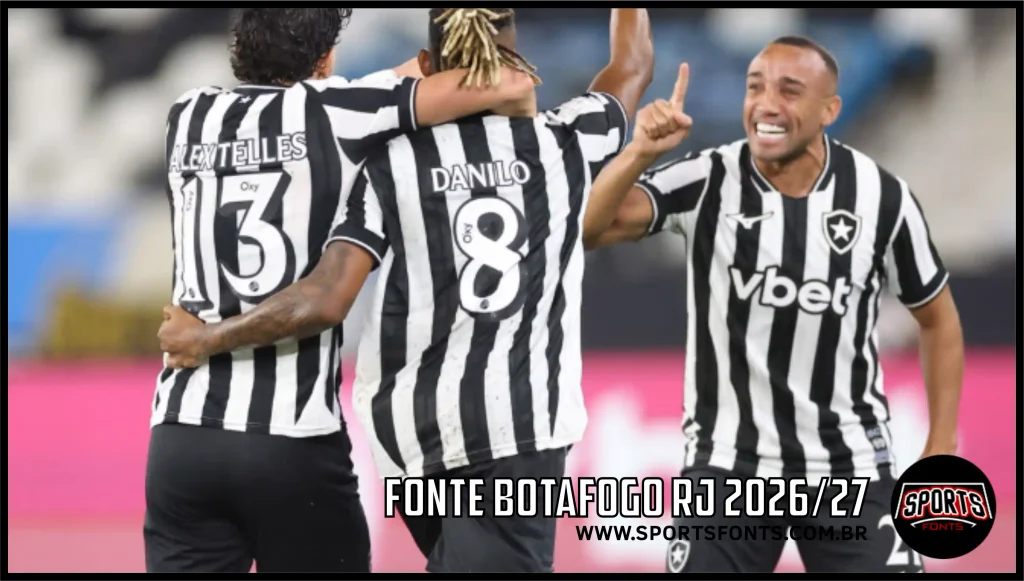
O Botafogo 2026/27 ganhou uma nova versão de sua tipografia esportiva no SportsFonts. Confira os números e letras vetorizados e faça o download gratuito para seus projetos.
Fonte Botafogo RJ 2026/27: versão vetorizada para download
Os torcedores do Botafogo de Futebol e Regatas que gostam de personalizar camisas e criar artes esportivas já podem conferir uma nova opção no SportsFonts: uma versão vetorizada da tipografia de nomes e números associada ao uniforme do clube na temporada 2026/27.
O material foi desenvolvido a partir da análise visual da numeração e das letras presentes na camisa, com o objetivo de reproduzir suas principais características gráficas e facilitar a utilização em projetos de design esportivo.
Características da tipografia Botafogo 2026/27
A numeração analisada apresenta um estilo esportivo marcante, com elementos que ajudam a destacar os algarismos nas costas da camisa.
Entre as características observadas estão:
• Algarismos com desenho esportivo e proporções características.
• Contornos marcantes ao redor dos números.
• Efeito de sombra lateral, proporcionando profundidade.
• Textura pontilhada no preenchimento.
• Elementos decorativos aplicados à parte inferior dos algarismos.
• Letras maiúsculas com serifas e aparência clássica.
A reprodução foi realizada por meio de um processo de vetorização, buscando preservar os detalhes visuais da referência utilizada.
Jogadores do botafogo de costa mostrando a fonte da camisa 2026/27
A versão vetorizada pode ser útil para estudos de tipografia esportiva, criação de artes, simulações de uniformes e trabalhos gráficos relacionados ao futebol.